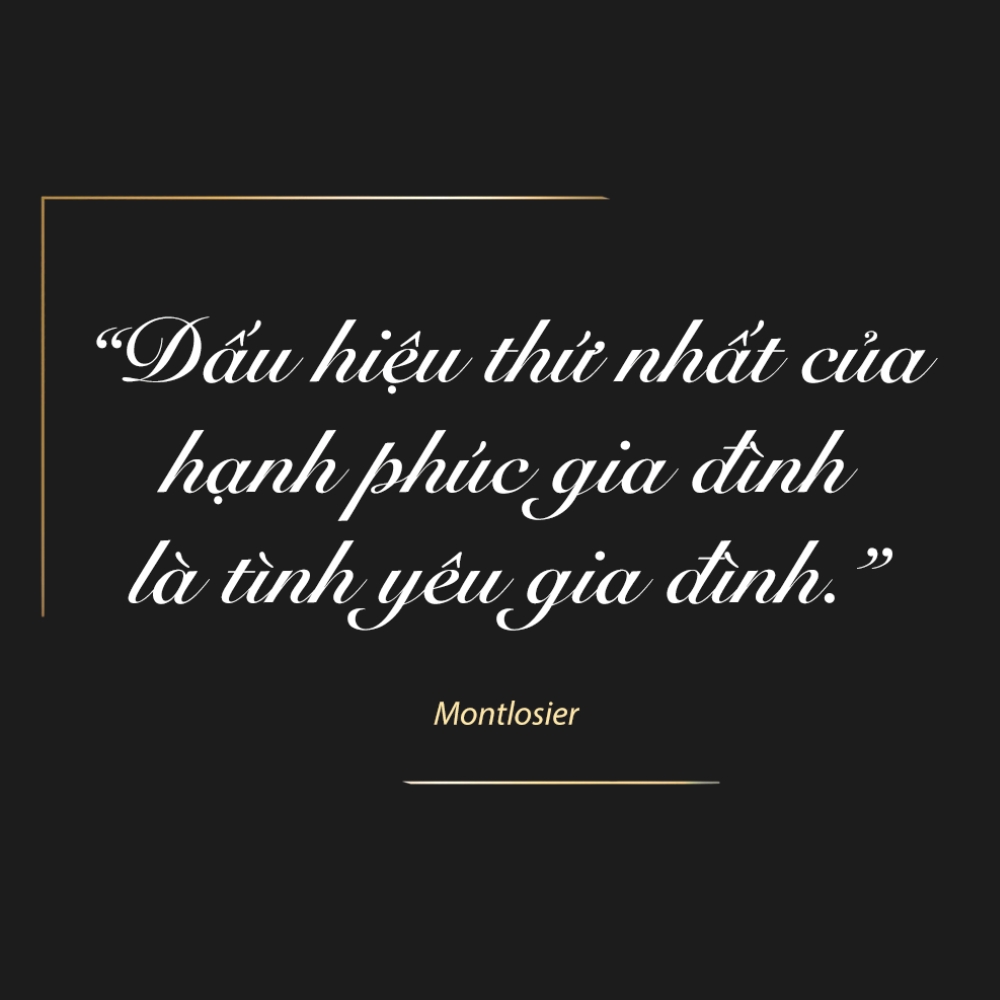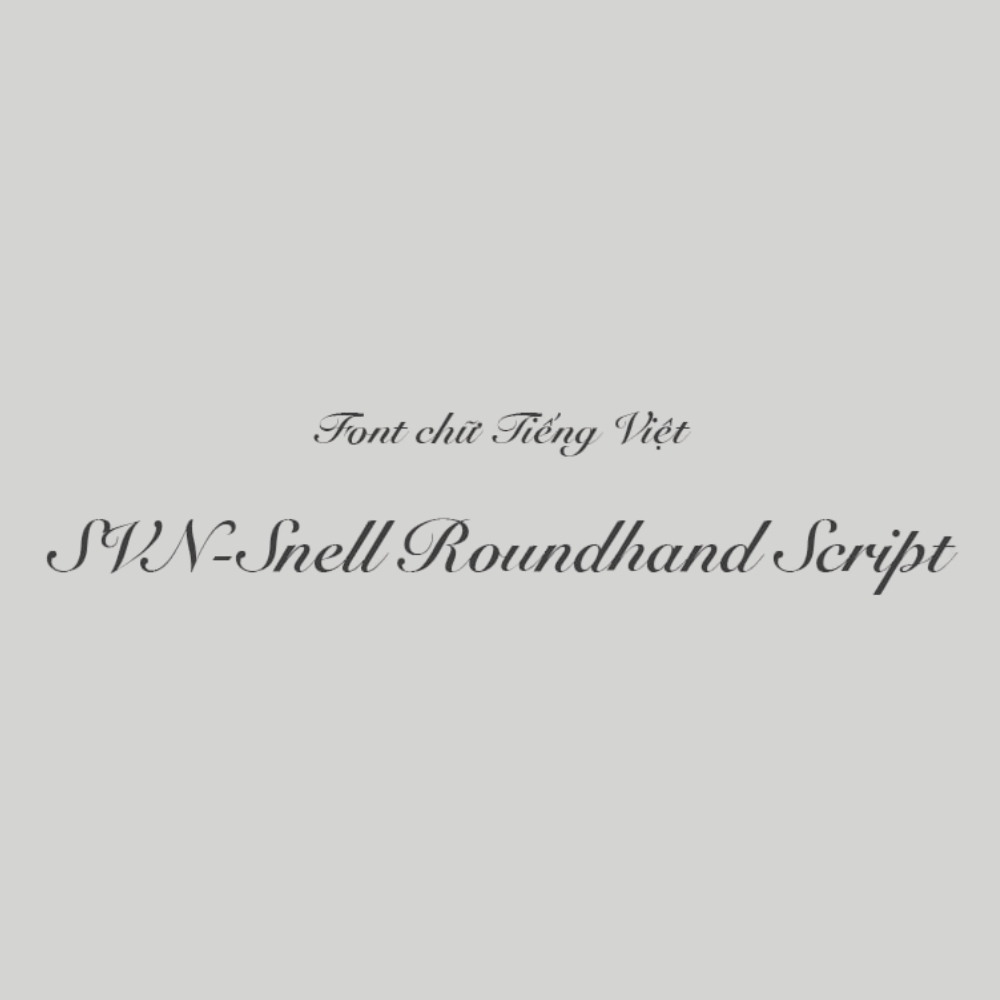
Tải 10+ font Việt hóa SVN Snell Roundhand Script cổ điển và đẹp mắt
Snell Roundhand Script là một trong những bộ font chữ mang phong cách thư pháp Anh cổ điển, nổi bật với những đường nét uốn lượn mảnh mai và sang trọng. Sự xuất hiện của font Việt hóa SVN Snell Roundhand Script mang lại một giải pháp trình bày văn bản đầy tính nghệ thuật cho người dùng tại Việt Nam, đặc biệt là trong các ấn phẩm đòi hỏi sự thanh lịch.
Vẻ đẹp nghệ thuật đặc trưng của bộ font Việt hóa SVN Snell Roundhand Script
Bộ font này mô phỏng kỹ thuật viết bút mực truyền thống với các nét thanh, nét đậm đan xen nhịp nhàng, tạo ra một dòng chảy tự nhiên cho văn bản. Khác với các dòng font script hiện đại có phần phóng khoáng, font chữ tiếng Việt SVN-Snell Roundhand Script giữ được cấu trúc chuẩn mực và sự cân đối giữa các ký tự. Việc tối ưu hóa bộ dấu tiếng Việt giúp các dấu thanh phối hợp hài hòa với độ cao của từng ký tự, duy trì tính thẩm mỹ xuyên suốt của bộ chữ gốc.
Sự tinh tế của Snell Roundhand Script còn nằm ở cách các chữ cái liên kết với nhau bằng những nét móc mềm mại. Đặc điểm này giúp văn bản sau khi trình bày mang lại cảm giác thủ công cao cấp, rất phù hợp để tạo điểm nhấn cho những mảng tường nội thất, bảng tên phòng khách sạn hoặc các ấn phẩm văn hóa mang hơi hướng cổ điển châu Âu. Đây là lựa chọn phù hợp cho các thiết kế cần sự chỉn chu và thể hiện đẳng cấp thẩm mỹ riêng.
Phân loại phong cách Calligraphy / English Roundhand
Mục đích phù hợp Tiêu đề, logo, thiệp mời, trang trí
Lời khuyên thiết kế: Do Snell Roundhand có nhiều nét uốn lượn và mảnh, bạn nên sử dụng ở kích thước trung bình trở lên để các chi tiết không bị nhòe. Việc phối hợp font này với một kiểu chữ Serif đứng (có chân) cổ điển sẽ giúp bản thiết kế của bạn trông chuyên nghiệp và cân bằng hơn.
03 Ứng dụng phổ biến của font SVN Snell Roundhand Script hiện nay
Với vẻ ngoài sang trọng và đậm chất nghệ thuật, bộ font chữ này mang lại giá trị cao khi được đưa vào thực tế trang trí và quảng bá các công trình mang phong cách cổ điển hoặc tân cổ điển:
• Nhận diện thương hiệu cho Resort & Spa: Những nét chữ thanh thoát của Snell Roundhand rất ăn ý khi xuất hiện trên logo hoặc bảng tên các khu nghỉ dưỡng, homestay container cao cấp, giúp tạo ra cảm giác thư giãn và chuyên nghiệp cho du khách.
• Thiết kế thiệp mời và Menu trang trọng: Sử dụng font chữ này cho tiêu đề chính trên các bản thực đơn nhà hàng hoặc thiệp mời sự kiện giúp nâng tầm giá trị cho ấn phẩm, thể hiện sự hiếu khách và tính thẩm mỹ của chủ nhân.
• Trang trí nội thất và Slogan nghệ thuật: Bạn có thể dùng font này để cắt chữ nổi laser trên vật liệu đồng, inox hoặc gỗ để trang trí tại sảnh chờ văn phòng hoặc phòng khách nhà lắp ghép nhằm tạo điểm nhấn đầy tinh tế.
03 Lưu ý kỹ thuật khi sử dụng font chữ tiếng Việt SVN-Snell Roundhand Script
Để khai thác hiệu quả vẻ đẹp của font chữ tiếng Việt SVN-Snell Roundhand Script mà không làm rối mắt người đọc, người thiết kế nên lưu tâm một số điểm sau:
• Tránh viết hoa toàn bộ cụm từ: Đặc trưng của font Calligraphy là nét nối giữa các chữ thường. Việc sử dụng toàn bộ chữ in hoa sẽ làm mất đi nhịp điệu của dòng chữ và gây khó khăn lớn cho việc nhận diện mặt chữ.
• Nới rộng khoảng cách dòng: Do các nét móc của font thường vươn rộng ra xung quanh, bạn cần để khoảng cách dòng thoáng một chút để các ký tự không bị chồng chéo lên nhau, giữ được sự minh bạch cho văn bản.
• Lựa chọn nền hiển thị phù hợp: Với các nét chữ mảnh, bạn nên đặt font trên những nền màu có độ tương phản cao hoặc nền trơn để các đường nét uốn lượn được hiển thị sắc sảo và rõ ràng.